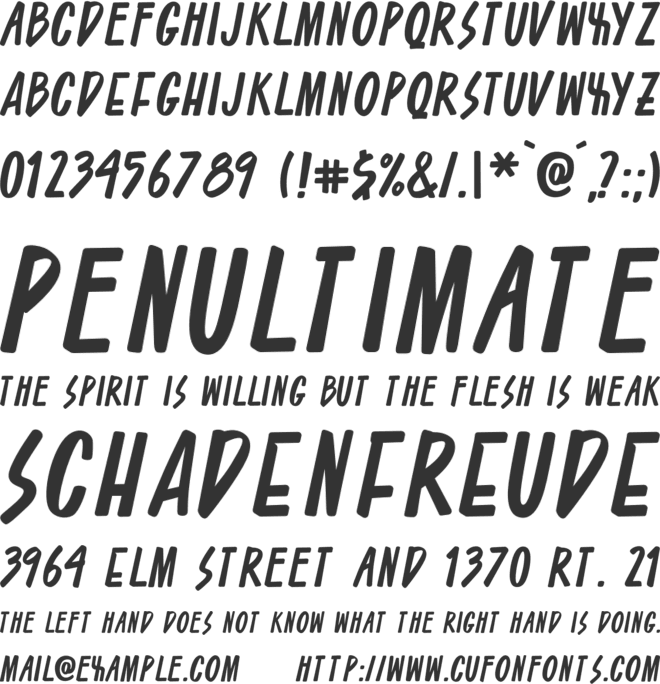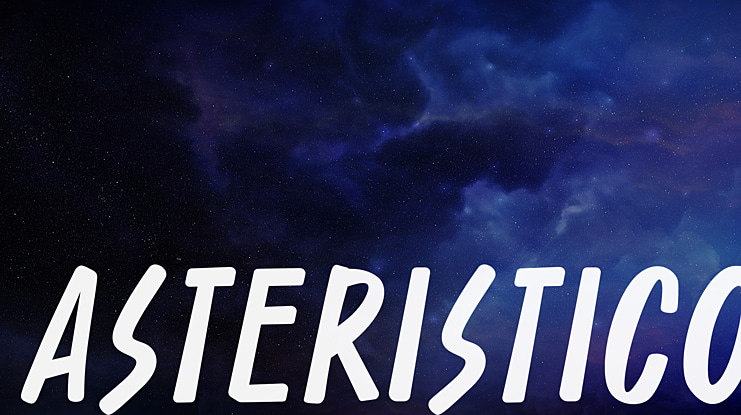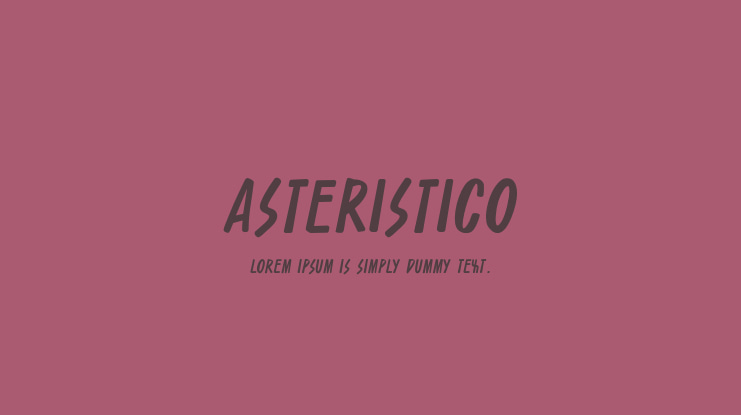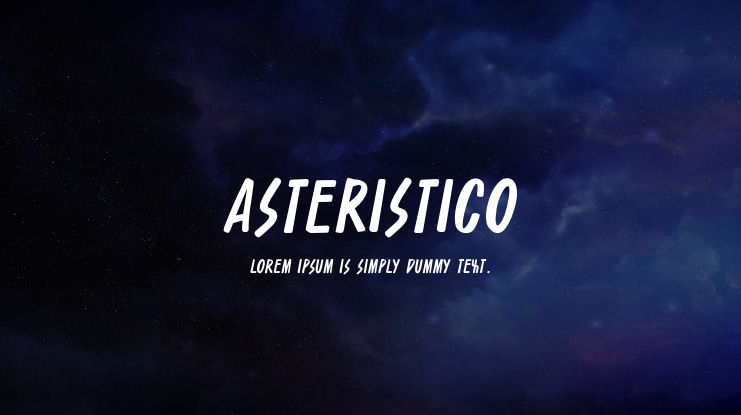
Asteristico Font
Nota do autor: Asterístico é uma tipografia digital de inspiração vernacular criada por Jonathan William Petroski para um trabalho acadêmico na UFPR (Universidade Federal do Paraná). As referências utilizadas para os caracteres são os letreiramentos urbanos encontrados na Cidade de Curitiba-PR/Brasil.
Author's note: Asterístico is a digital type inspired by vernacular design, created for an academic work at UFPR (Federal University of Paraná). The references used for the types are the urban hand lettering sign found in the City of Curitiba-PR / Brazil.